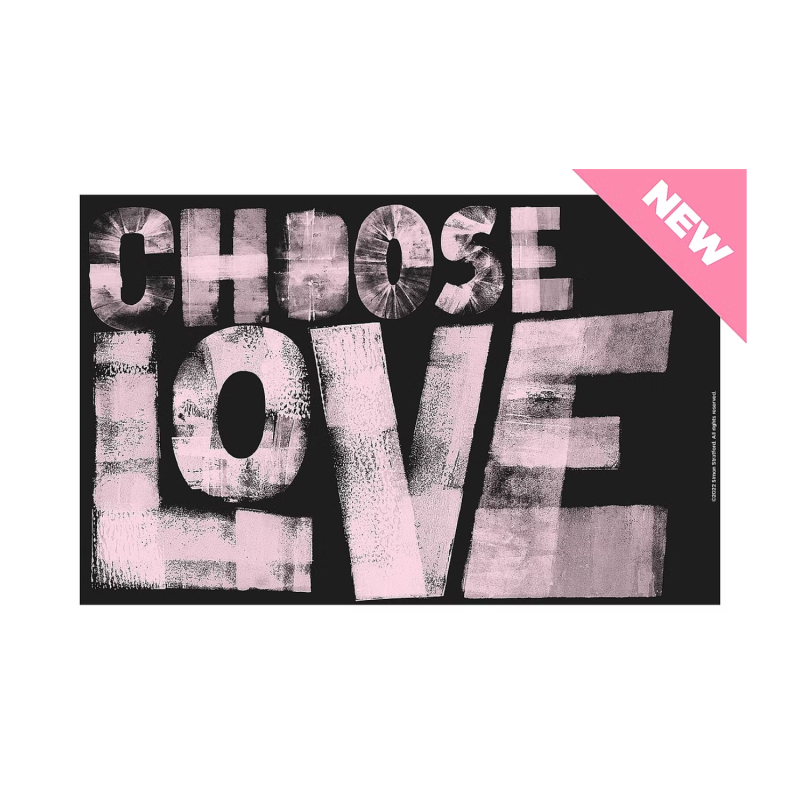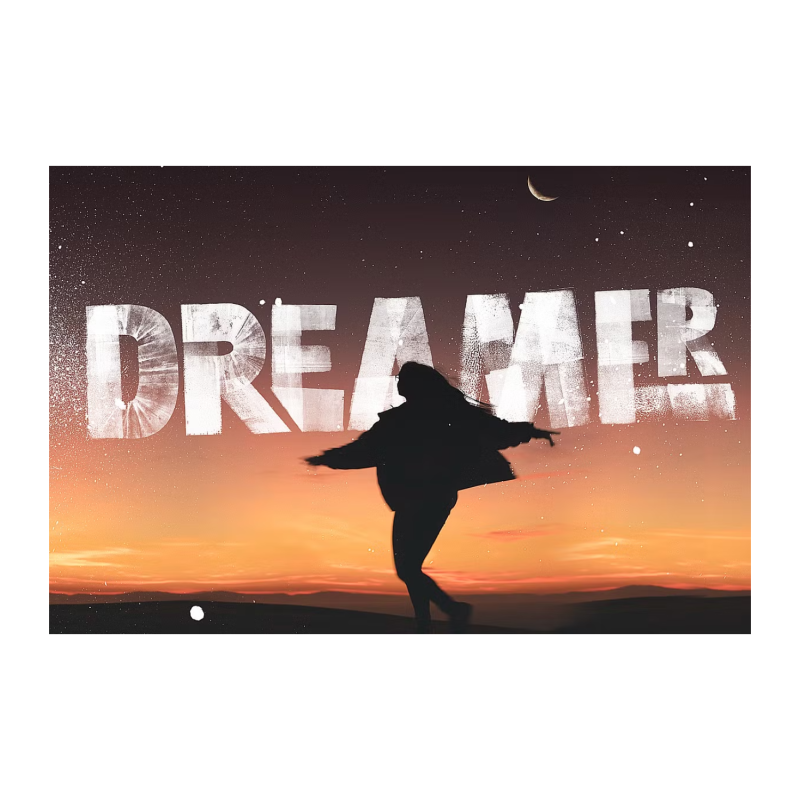
عرض الخط اختر الحب بلا رقيق
• اختر محرف الحب بواسطة سيمون ستراتفورد. خط عرض بالحبر المتسخ مستوحى من الحروف مطبوع يدويا ومليء بتفاصيل الطباعة الرائعة.
• تم إنشاء الخط باستخدام قواطع من الورق المقوى وبرايير حبر ثم طباعته على الورق ، لذا فهو مصنوع يدويا.
• التفاصيل من علامات طباعة الحروف مذهلة للغاية. سيكون من الصعب عليك العثور على محرف مطبوع يدويا أفضل مثله.
• إنه جريء. إنه أبعد ما يكون عن الكمال. إنه مليء بالعيوب والعلامات القذرة - بالطريقة التي أحبها.